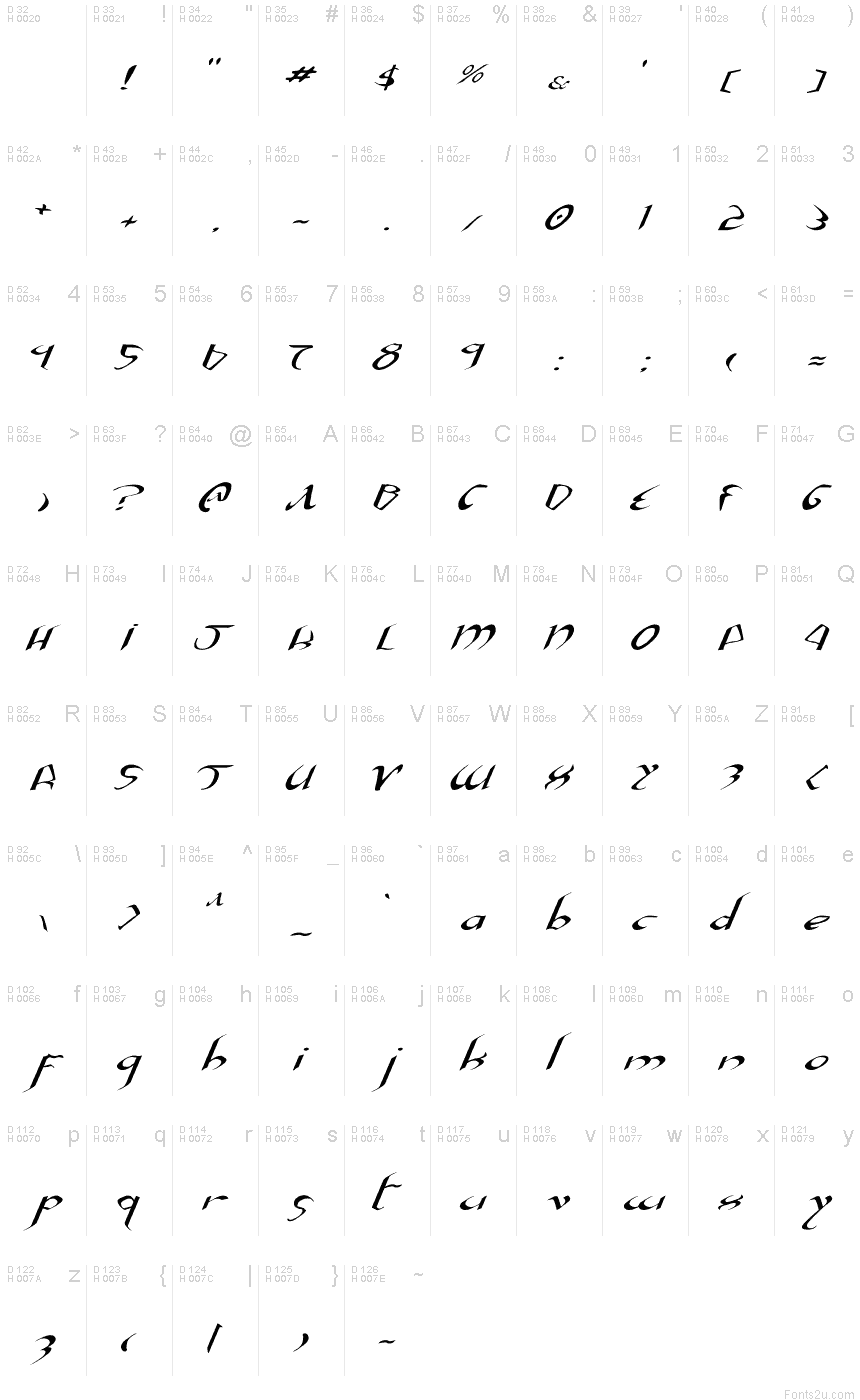
Anteprima del carattere Xaphan II Expanded Italic
Xaphan II Expanded Italic, di Iconian Fonts, è un carattere gotico corsivo gratuito dal ritmo slanciato, quasi tagliente, con un’inconfondibile impronta medievale. Le lettere combinano tratti ad uncino e curve ampie che si assottigliano; lo stile richiama più una blackletter reinterpretata attraverso una calligrafia veloce che una scrittura antica e rigida.
Si adatta perfettamente al branding fantasy, ai loghi per videogiochi, ai flyer metal, alle copertine di libri e ai titoli, dove serve un carattere gratuito con un tono oscuro e cerimoniale, senza però diventare un semplice ornamento fine a se stesso. Grazie ai tratti che si allungano in punte acuminate e curve improvvise, funziona benissimo anche per titoli brevi, iniziali e monogrammi che richiedono tanto movimento quanto drammaticità.